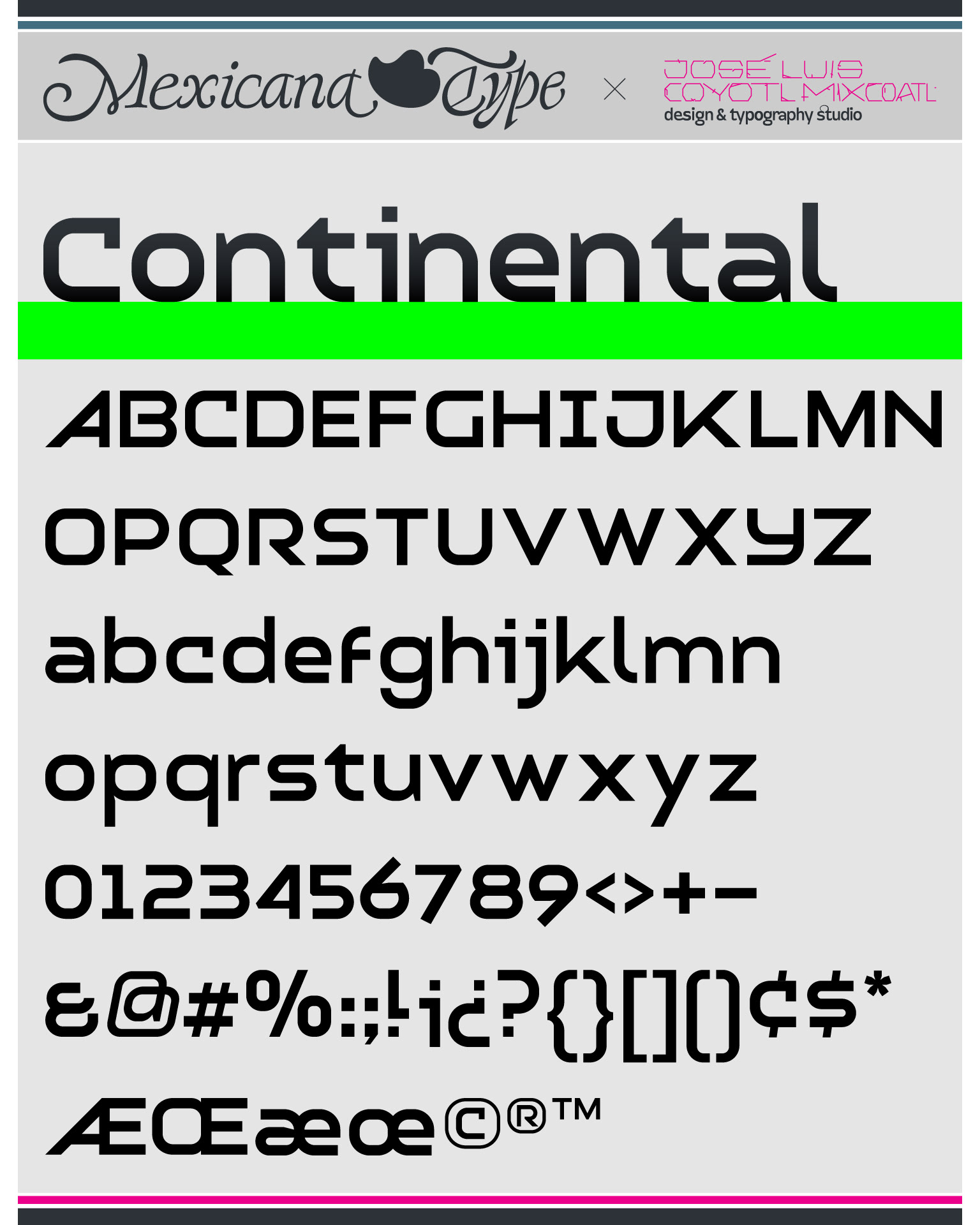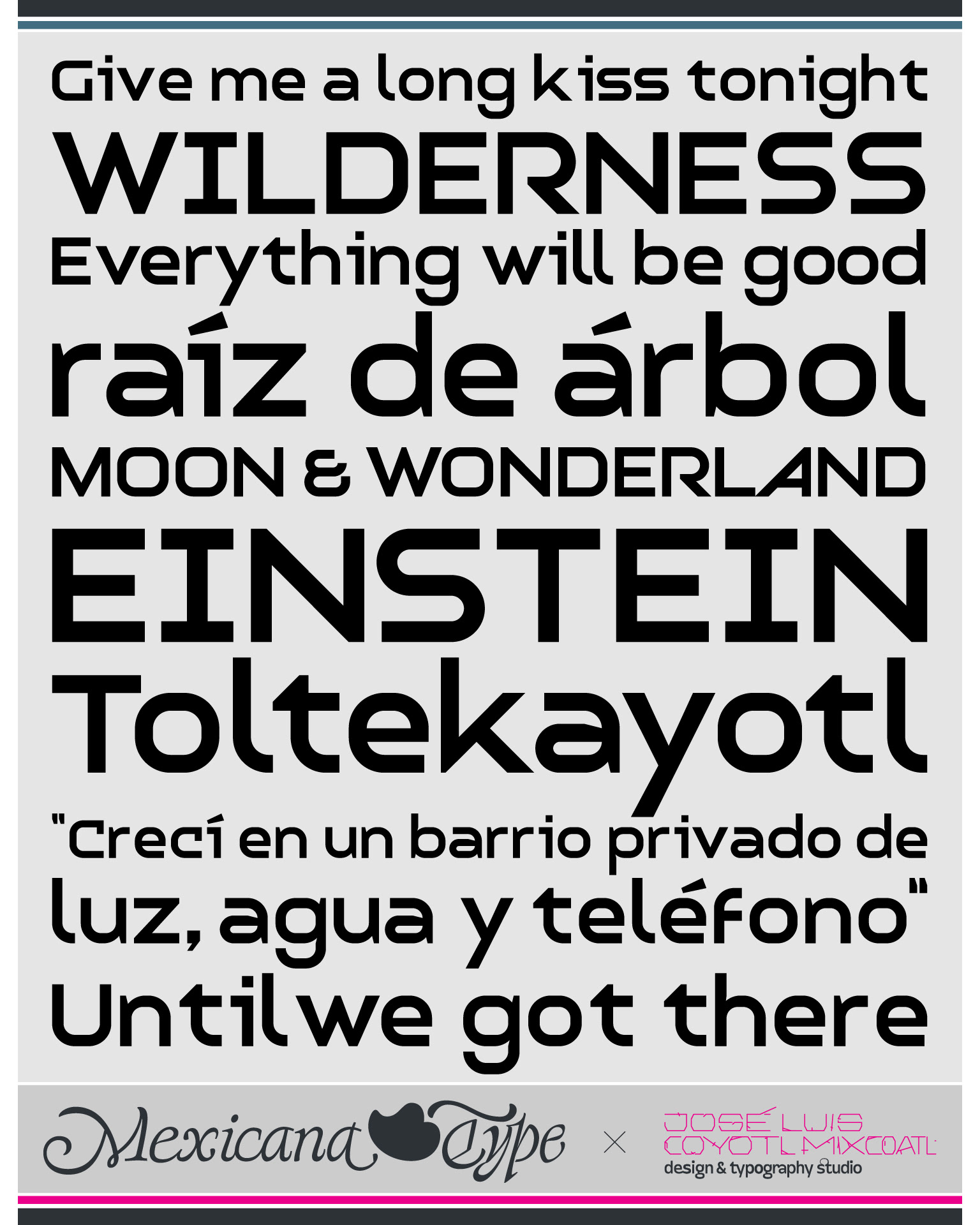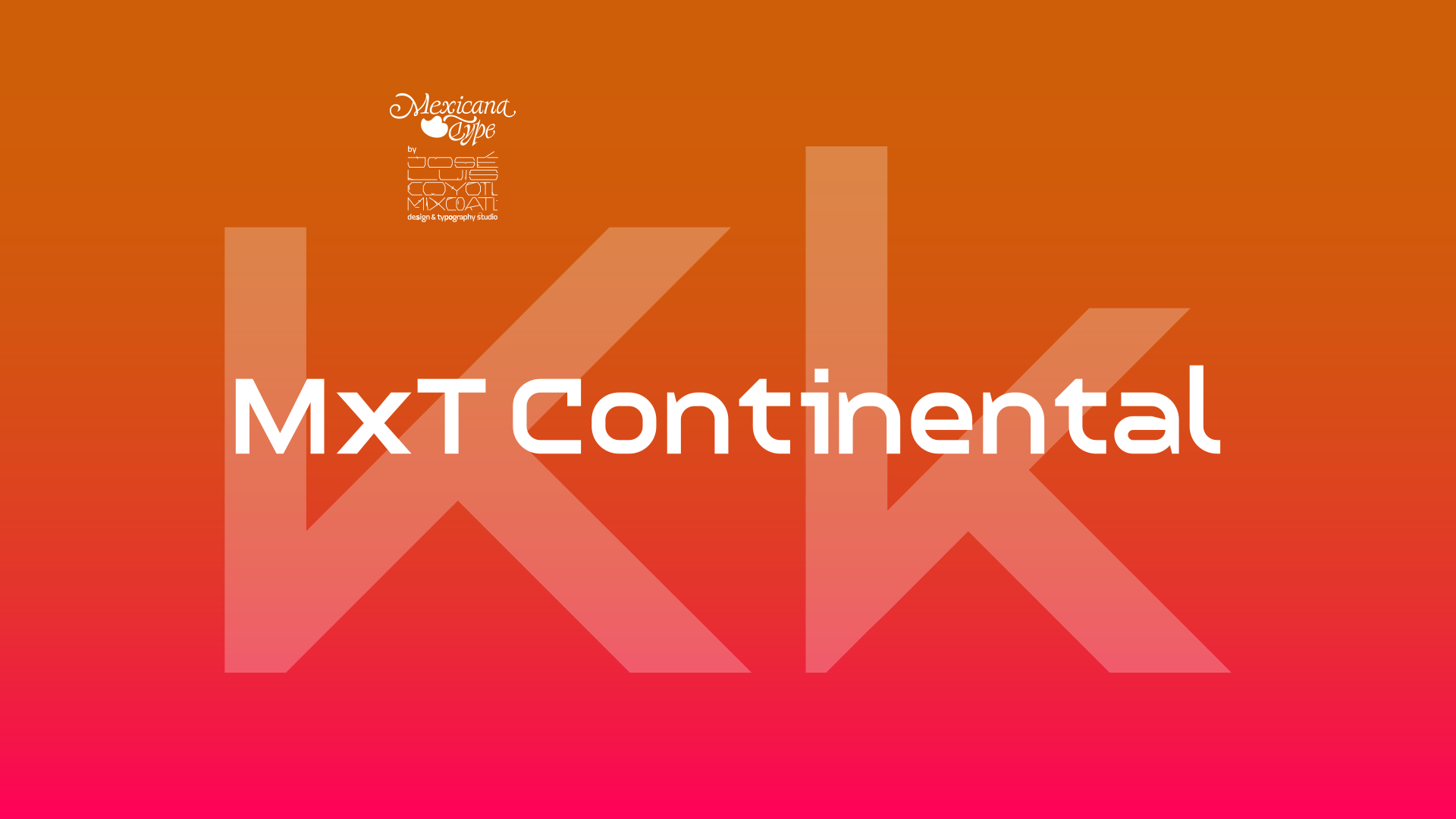
MxT Continental fue desarrollada especialmente para ser grabada en metal en puntajes pequeños en una serie de monedas conmemorativas y para uso en títulos para promocionales de éstas. El reto principal fue hacer un desarrollo que pudiese adaptarse al medio impreso y al grabado sobre metal manteniendo el detalle, un buen grado de lectura y por supuesto con la sobriedad para la cuál fue diseñada, con el diseño de una tipografía casi unilineal y modular, de trazos geométricos y firmes, con espacios blancos amplios y extendida para ganar cuerpo pues no se tenia el impedimento de que se fuera a utilizar en composiciones y textos largos.